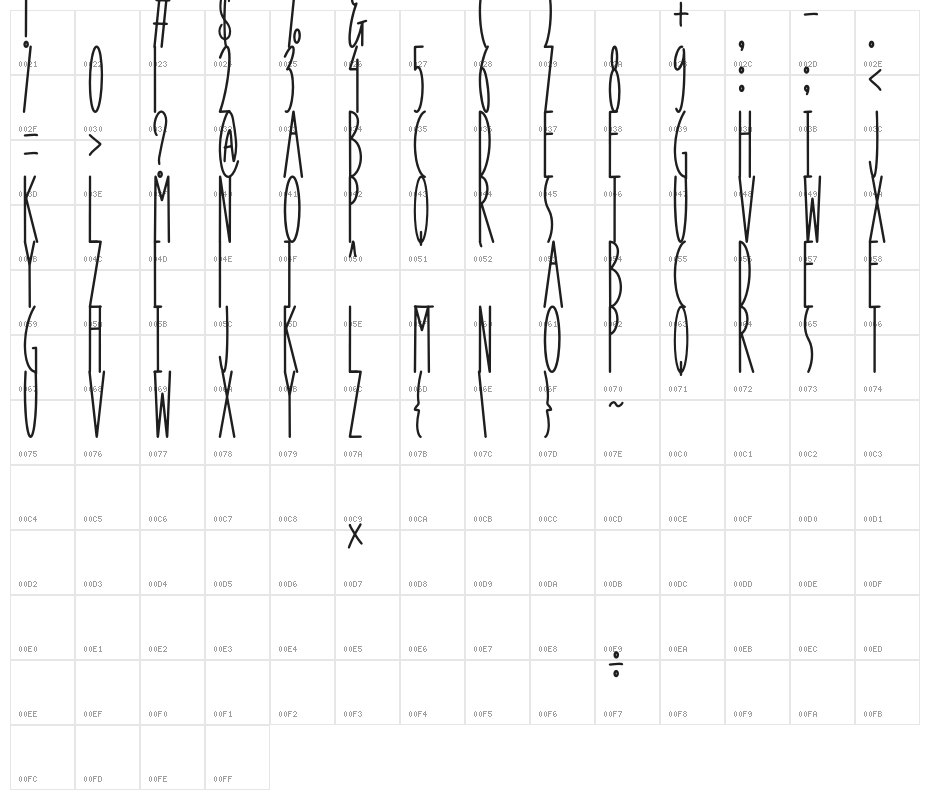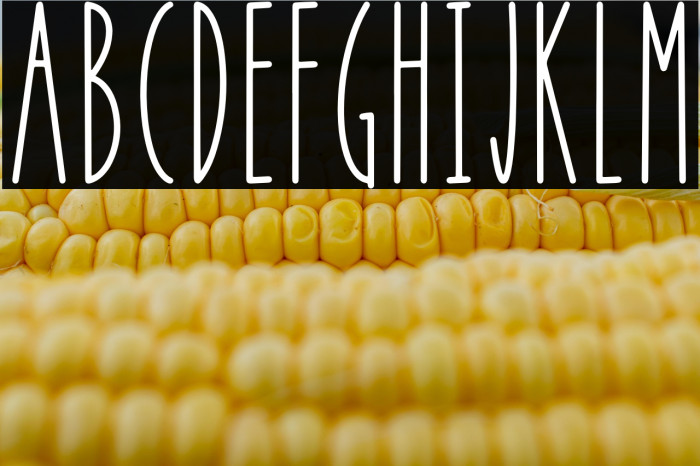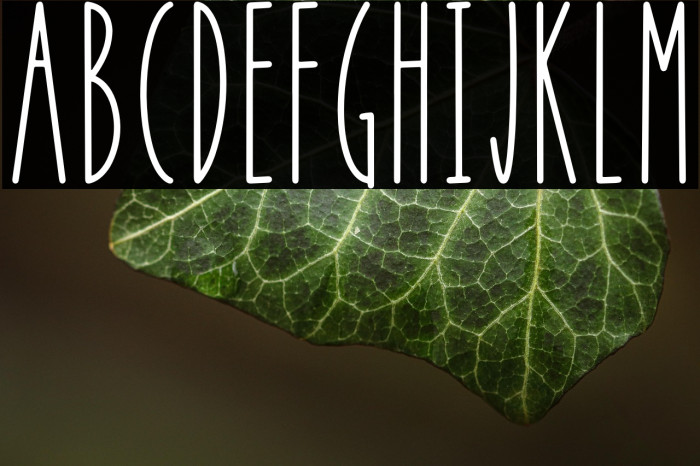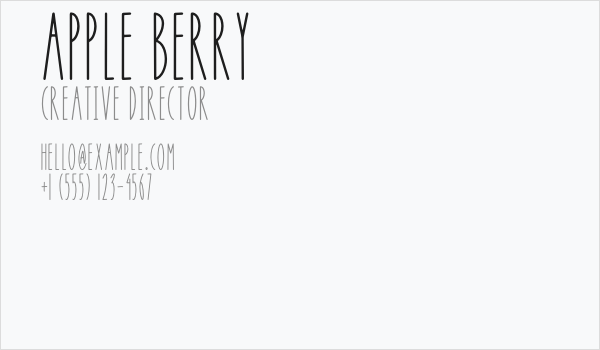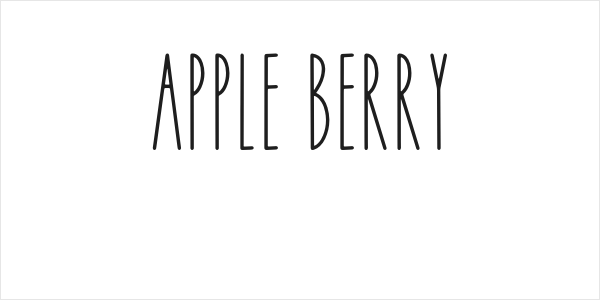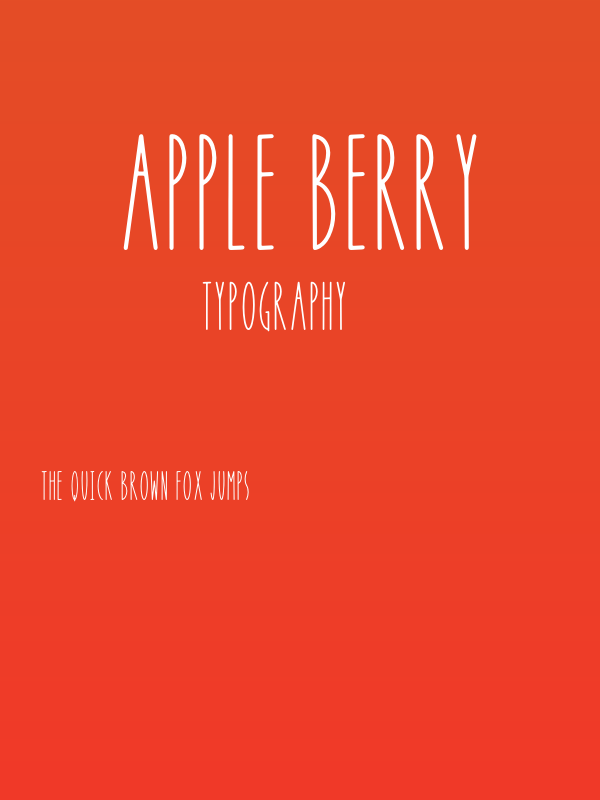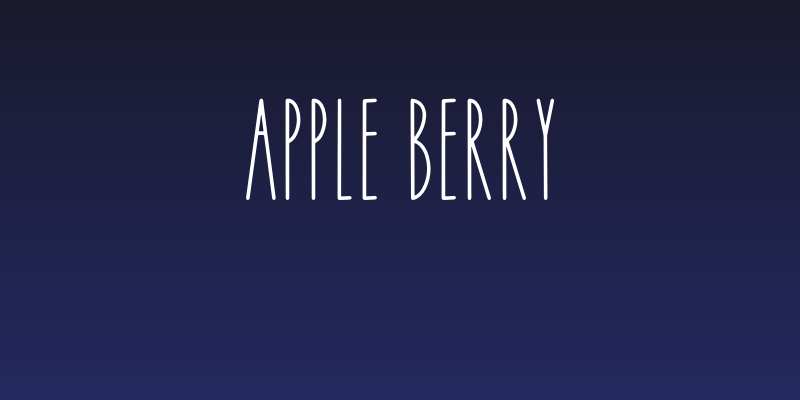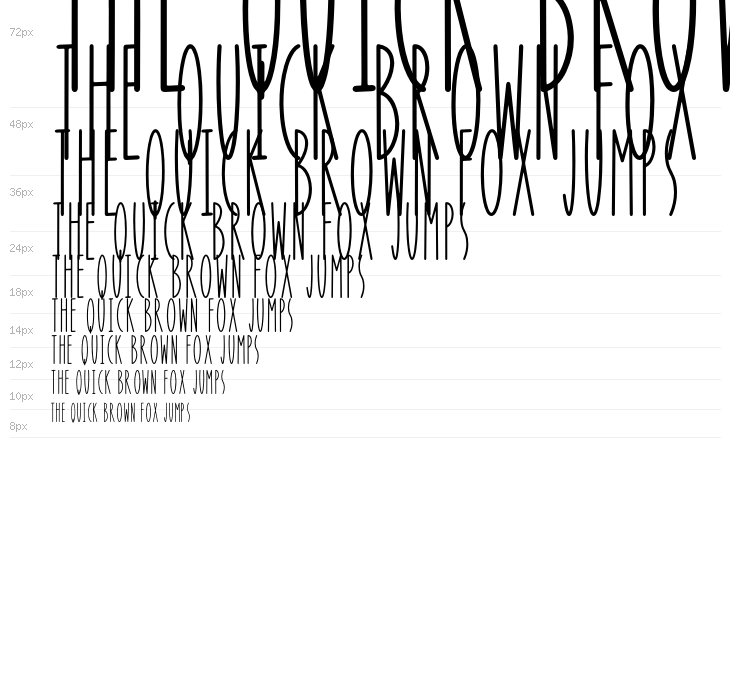
APPLE BERRY Font
| 宽度 | Condensed |
| 推荐项目 | Ideal for creative projects such as posters, album covers, and artistic branding where a distinctive and modern look is desired. |